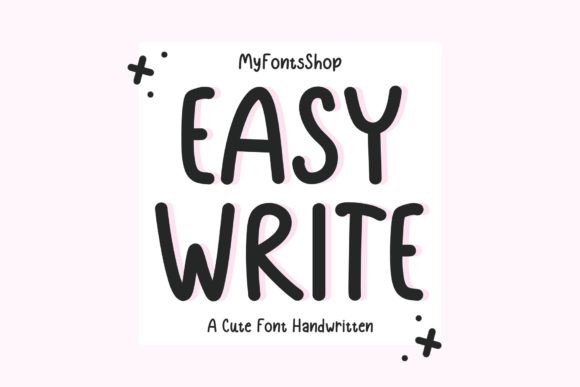
Easy Write
Easy Write: A Fonte Manuscrita que Transforma Ideias em Arte
Se você está em busca de uma tipografia que combine doçura e amigabilidade, a Easy Write chega como a escolha perfeita. Seu estilo manuscrito natural traz um toque humano a qualquer projeto, seja ele digital ou impresso. Vamos descobrir por que essa fonte está conquistando designers, criadores de conteúdo e pequenos negócios.
Principais Características da Easy Write
- Aspecto manuscrito autêntico – Cada letra foi desenhada à mão, garantindo um visual único e orgânico.
- Versatilidade – Ideal para convites, cartões, branding, posts de redes sociais, blogs e até apresentações corporativas.
- Leitura agradável – O espaçamento e a altura das linhas foram otimizados para manter a clareza, mesmo em textos mais longos.
Por que a Easy Write é a Escolha Certa para Seu Projeto?
O grande diferencial da Easy Write está na sua capacidade de se adaptar a diferentes estilos visuais. Precisa de algo fofinho para um convite de aniversário? Use a Easy Write para transmitir calor e proximidade. Quer dar um toque descontraído a um post de blog? A fonte adiciona personalidade sem perder profissionalismo.
Além disso, a aparência “handwritten” da Easy Write ajuda a criar conexões emocionais com o público, pois remete à escrita à mão, que ainda é associada a sinceridade e autenticidade.
Dicas de Uso para Potencializar Seu Design
- Combine Easy Write com fontes sans-serif neutras (como Montserrat ou Open Sans) para equilibrar elegância e legibilidade.
- Use cores suaves – tons pastel ou aquarela – para reforçar a sensação amigável da tipografia.
- Aplique a fonte em headings, citações e chamadas de ação; mantenha o corpo do texto em fontes mais neutras para evitar fadiga visual.
- Explore efeitos de textura, como papel reciclado ou fundo de quadro negro, para destacar ainda mais o estilo manuscrito.
Com um design natural e único, a Easy Write abre um leque ilimitado de possibilidades criativas. Seja para projetos pessoais ou para fortalecer a identidade visual da sua marca, esta fonte oferece a combinação ideal de charme e versatilidade. Não deixe sua imaginação limitada – experimente a Easy Write hoje mesmo e veja como ela pode transformar suas ideias em verdadeiras obras de arte.